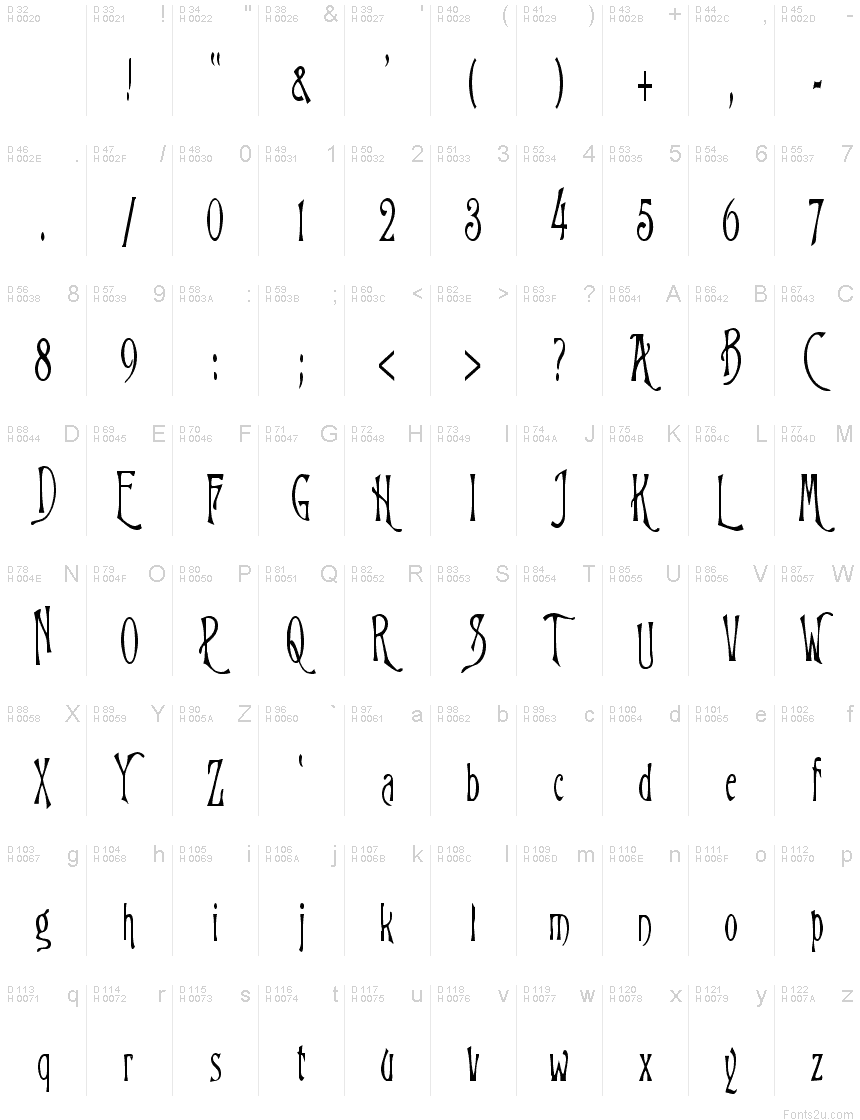
Wizard Condensed od SWFTE International to darmowy krój gotycki z nutką baśniowej magii. Litery są wysokie i wąskie, o ostrych, zwężających się liniach, z haczykowatymi zakończeniami i lekko ekscentrycznym rytmem, dzięki czemu styl ten przypomina bardziej napisy w stylu fantasy niż surowe średniowieczne pismo.
Świetnie sprawdza się na okładkach książek, w logotypach gier, plakatach festiwalowych, menu tematycznych czy planszach tytułowych, gdzie darmowy krój ma nadać starodawny klimat bez wrażenia ciężkości. Ponieważ formy są smukłe i żywe, pasują również do krótkich nagłówków, otwarć rozdziałów i inicjałów w stylu monogramu, którym potrzeba odrobiny magii zamiast surowego, historycznego dramatyzmu.